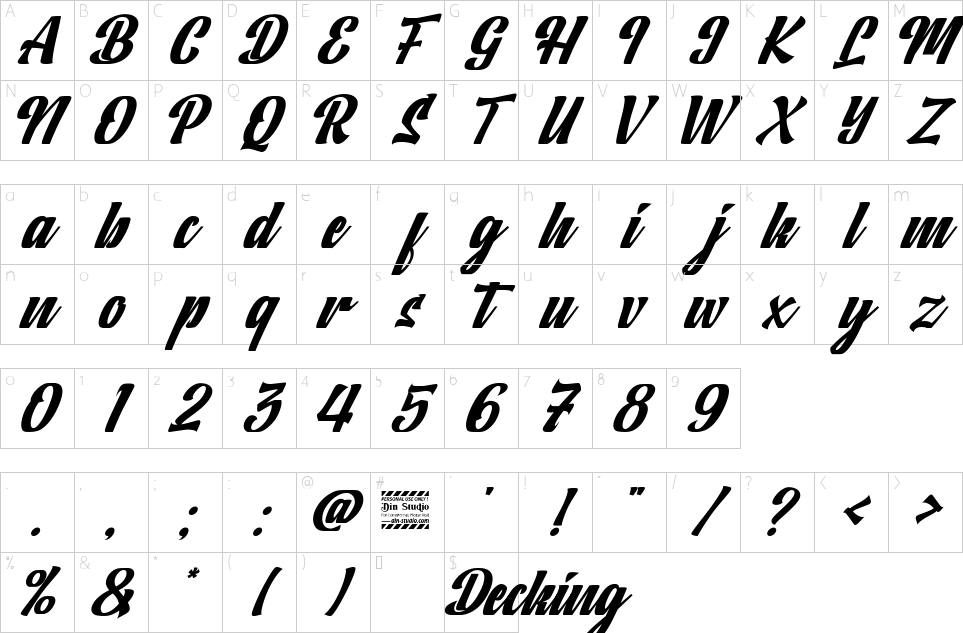
A Decking Font é uma elegante e moderna opção para quem busca qualidade em suas criações digitais. Desenvolvida pelo designer Donis Miftahudin, esta fonte foi projetada especificamente para atender às necessidades dos designers gráficos, oferecendo linhas atraentes e facilidade de uso. Com sua interface intuitiva, é uma excelente escolha tanto para o Windows quanto para o Mac, permitindo que você personalize suas criações com precisão e estilo. Esta fonte já foi baixada mais de 577 vezes por profissionais da indústria, demonstrando sua eficácia em diversas aplicações. Se você busca uma fonte confiável para seus projetos digitais, a Decking Font é uma ótima opção.